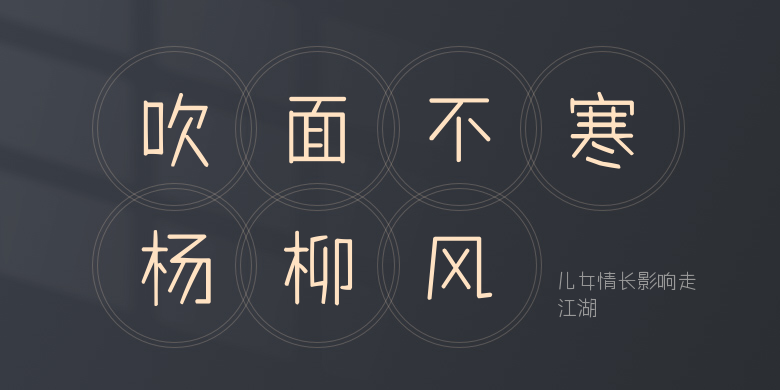
儿女情长影响走江湖
儿女情长影响走江湖,这款字体结构工整、笔画清晰,兼顾美观与易读性,适用于标题、正文、海报、包装、LOGO 等多种场景。字形优雅稳定,风格百搭耐看,适配日常排版与创意设计,让文字呈现更舒适、更具质感。儿女情长影响走江湖一笔一画,皆是细节,以均衡的比例、流畅的线条打造舒适视觉体验,字形端正大气,风格简约现代。无论是商业设计、品牌宣传还是日常排版,都能轻松驾驭,让文字更有格调与力量。儿女情长影响走江湖字体下载。